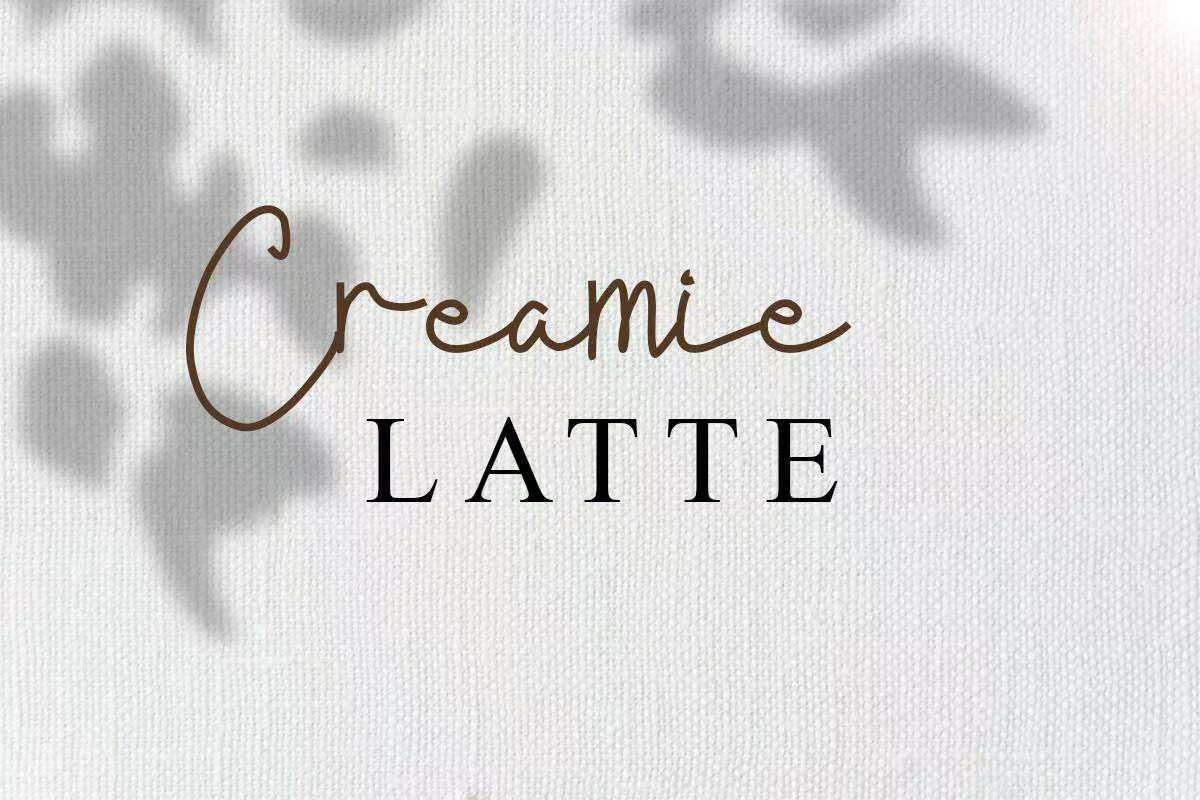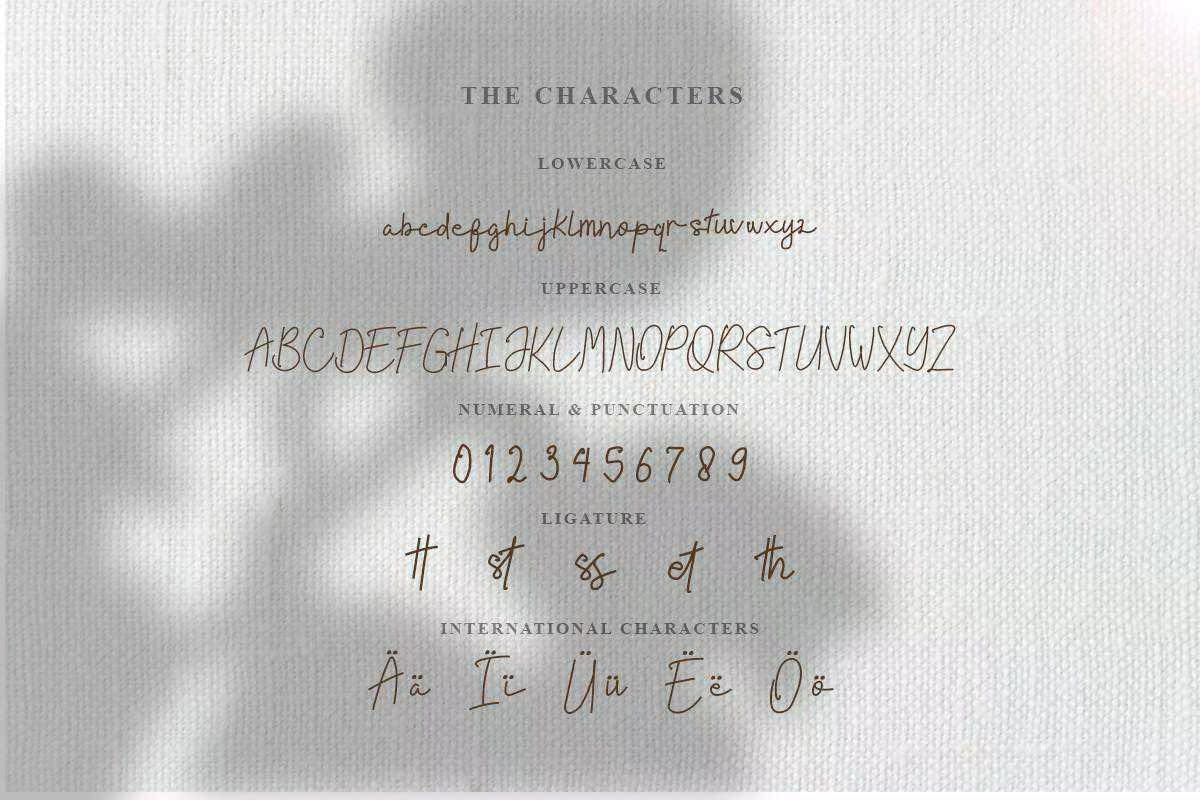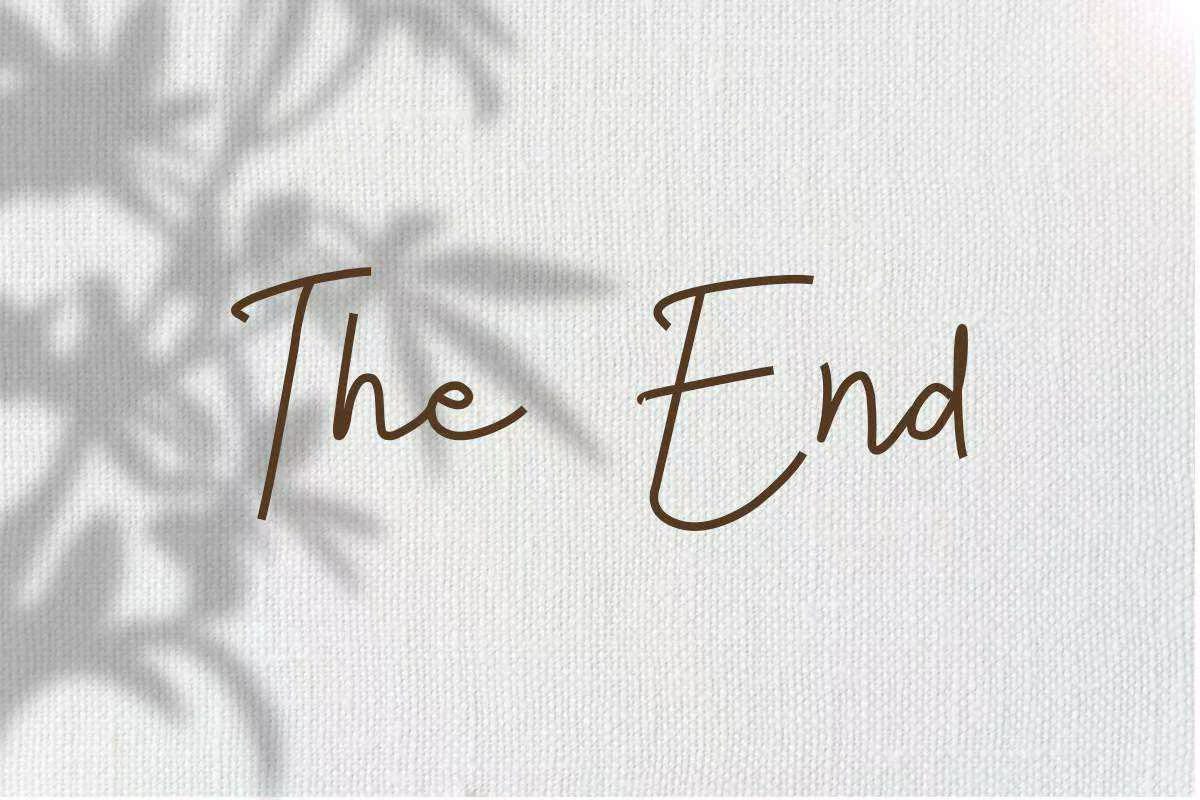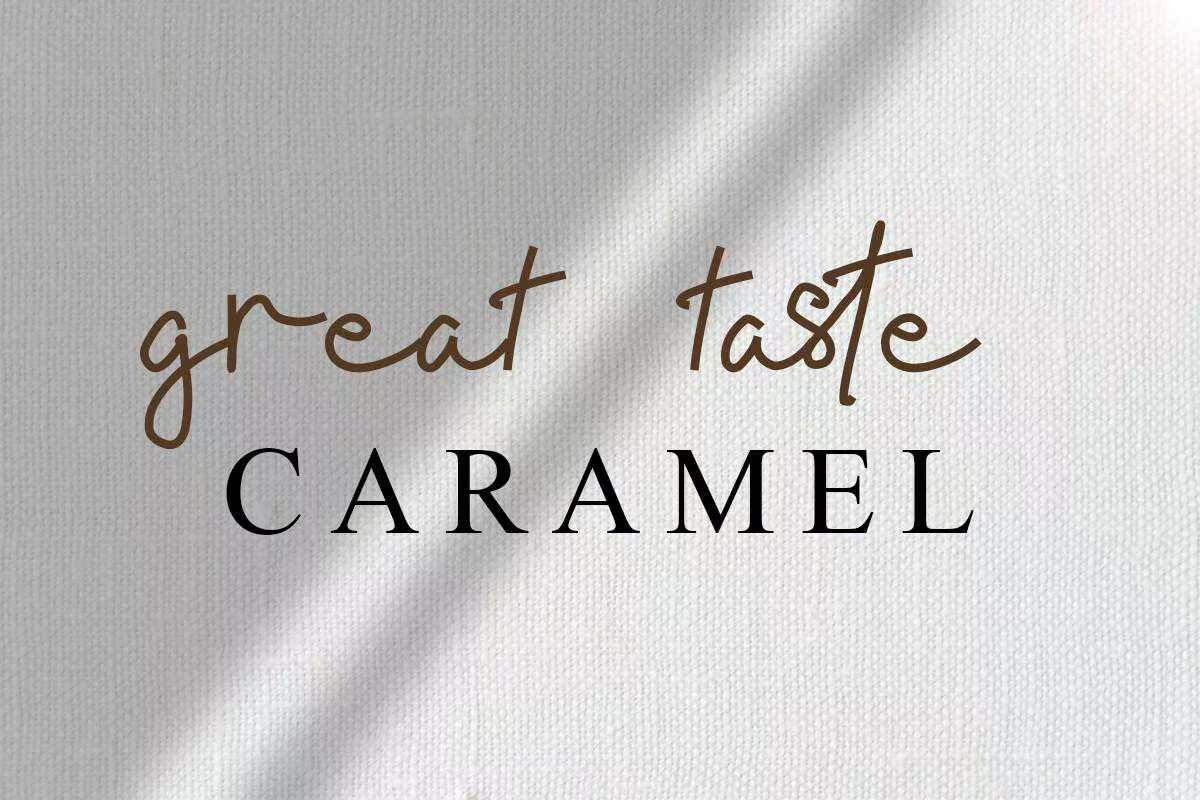
HELAVIONITAISAHANDWRITETENMONINEFONT具有自然优雅的感觉,适用于您的商业项目、婚礼设计、社交媒体、广告、产品包装、产品设计、标签、摄影、水印、邀请、,文具商和需要手写单品的项目。HelavionittaisahandWritenMonolineFont具有自然和优雅的感觉,适用于您的商业项目,如GO、婚礼设计、社交媒体、广告、产品包装、产品设计、标签、摄影、水印、邀请函、文具商和需要手写单品的项目。